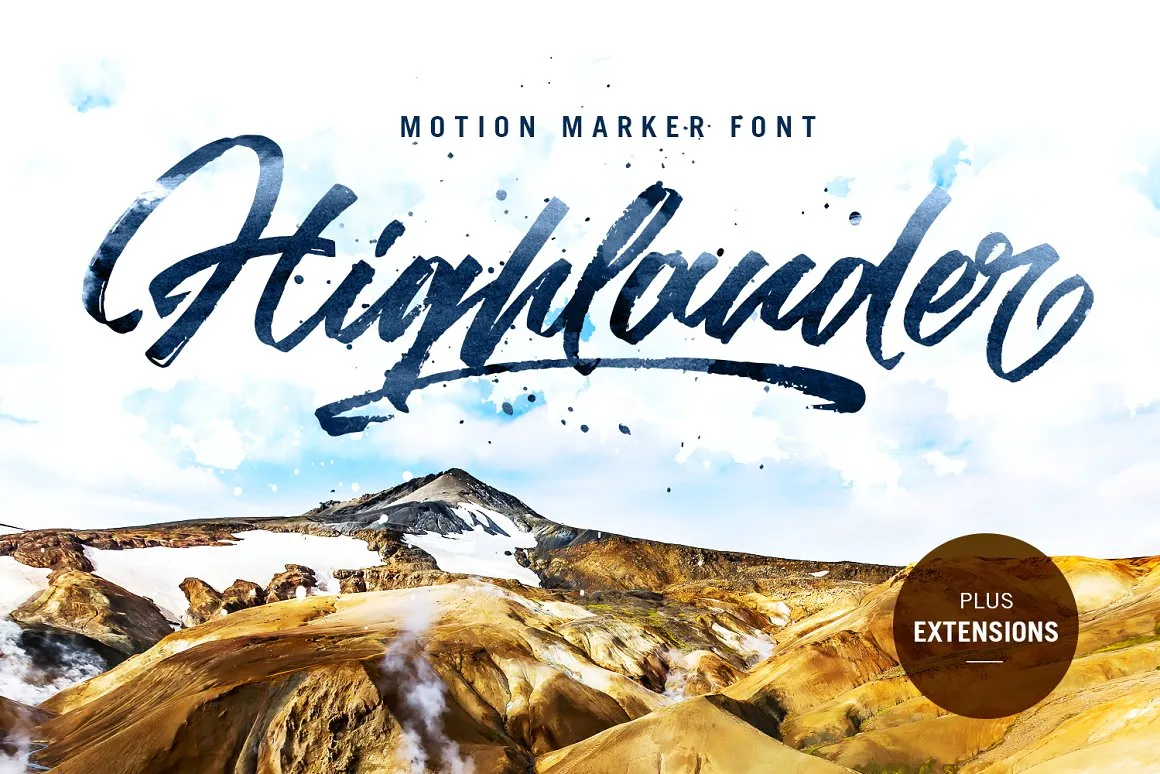
Highlander Brush Font – Fonte Grátis
Highlander Brush Font
Descubra a arte única da Highlander Brush Font, uma seleção premium de letras feitas por Kavoon. Esta elegante fonte é perfeita para quem busca uma mistura cuidadosa entre script e gráficos. Highlander vem com um conjunto completo de caracteres maiúsculas e minúsculas, dando-lhe a liberdade para transformar seu texto em artesanato personalizado à mão. A Highlander inclui um vasto leque de símbolos, como números, pontuação e suporte multilíngue. Além disso, acompanha uma extra fonte com extras de extensões projetadas para complementar perfeitamente sua fonte principal. Esta fonte é especialmente adequada para designers que buscam um elemento diferenciador em seus trabalhos de design gráfico, seja para marcas, logotipos ou textos. A Highlander Brush Font é uma ótima escolha para quem busca manter a elegância do tipo tipográfico clássico sem perder o toque artístico personalizado que o script oferece. Com Highlander, você transforma seu design em um trabalho de arte autêntico e único.